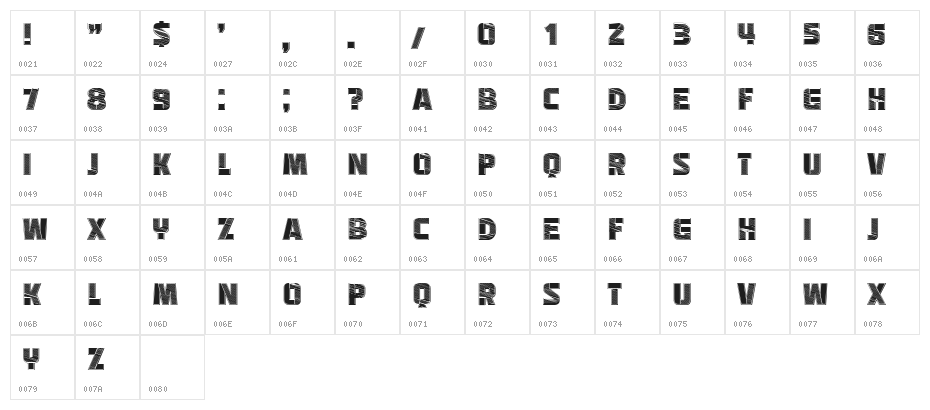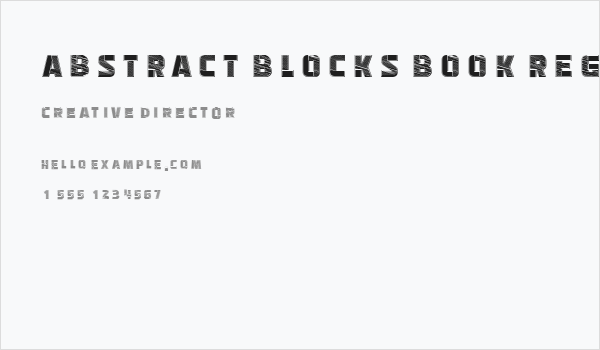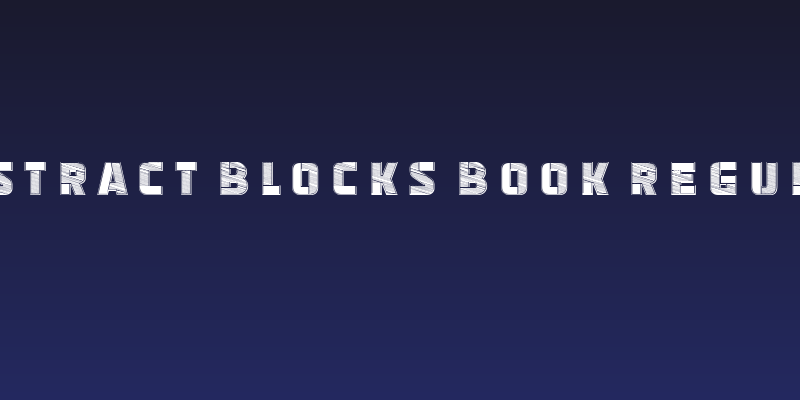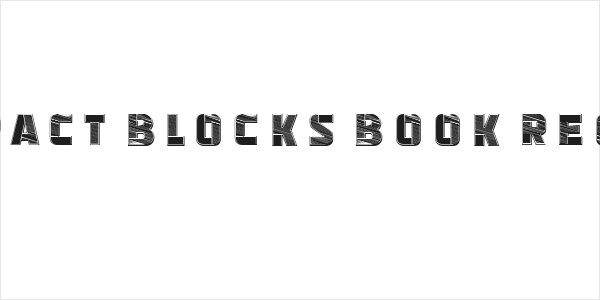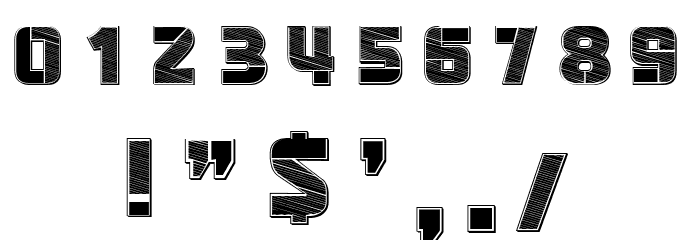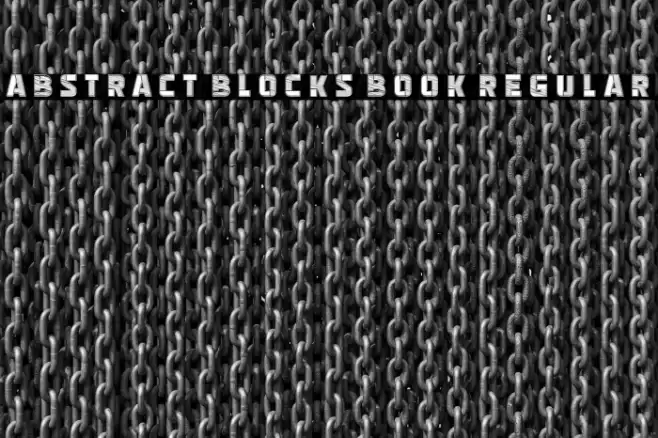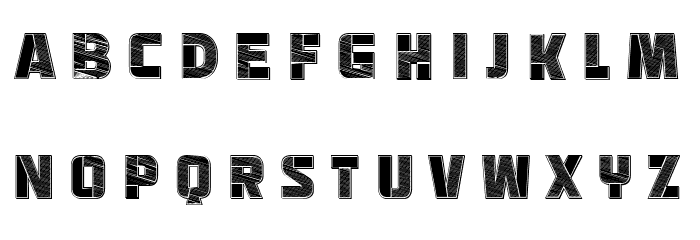
Abstract Blocks Book Regular Font
| 全体的なスタイル | Modern, Industrial |
| おすすめプロジェクト | Ideal for posters, logos, branding materials, and any project requiring a strong, modern aesthetic. |